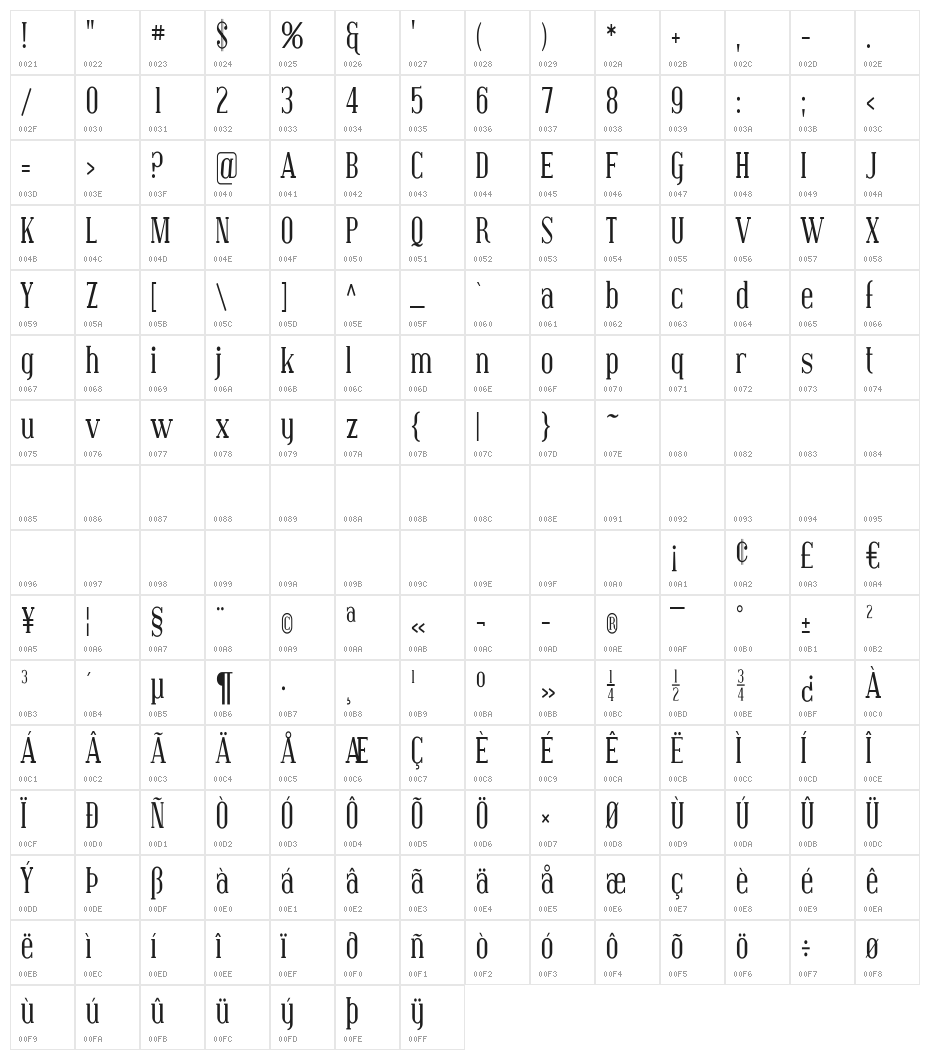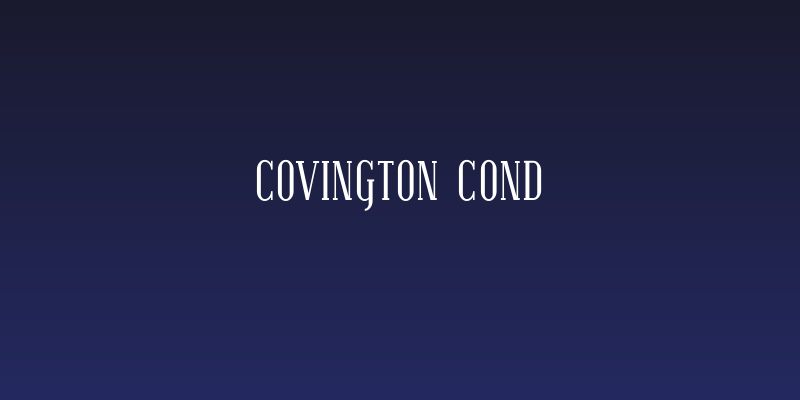
Covington Cond Font
✎ Serif
| 分类 | Serif |
| 宽度 | Condensed |
| 整体风格 | Classic |
| 使用场景 | Headlines, Editorial design, Branding |
| 推荐项目 | This font is perfect for editorial design, book covers, formal invitations, and branding materials that require a touch of elegance and sophistication. |